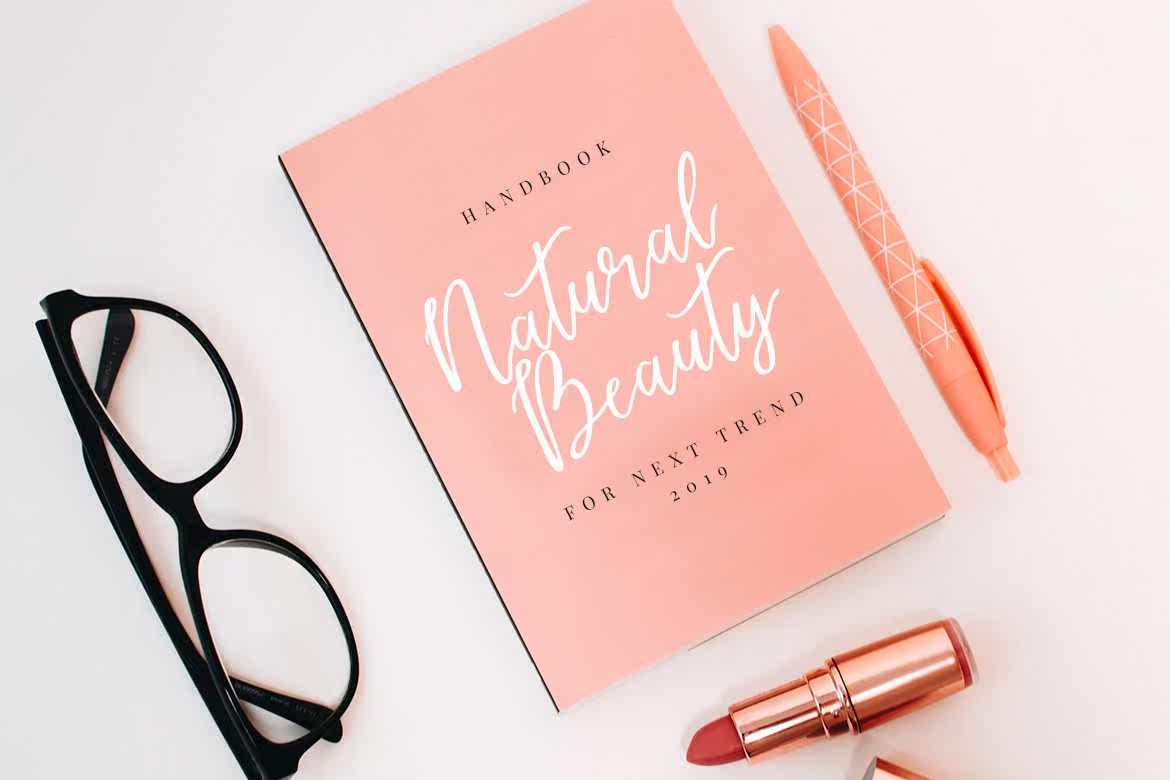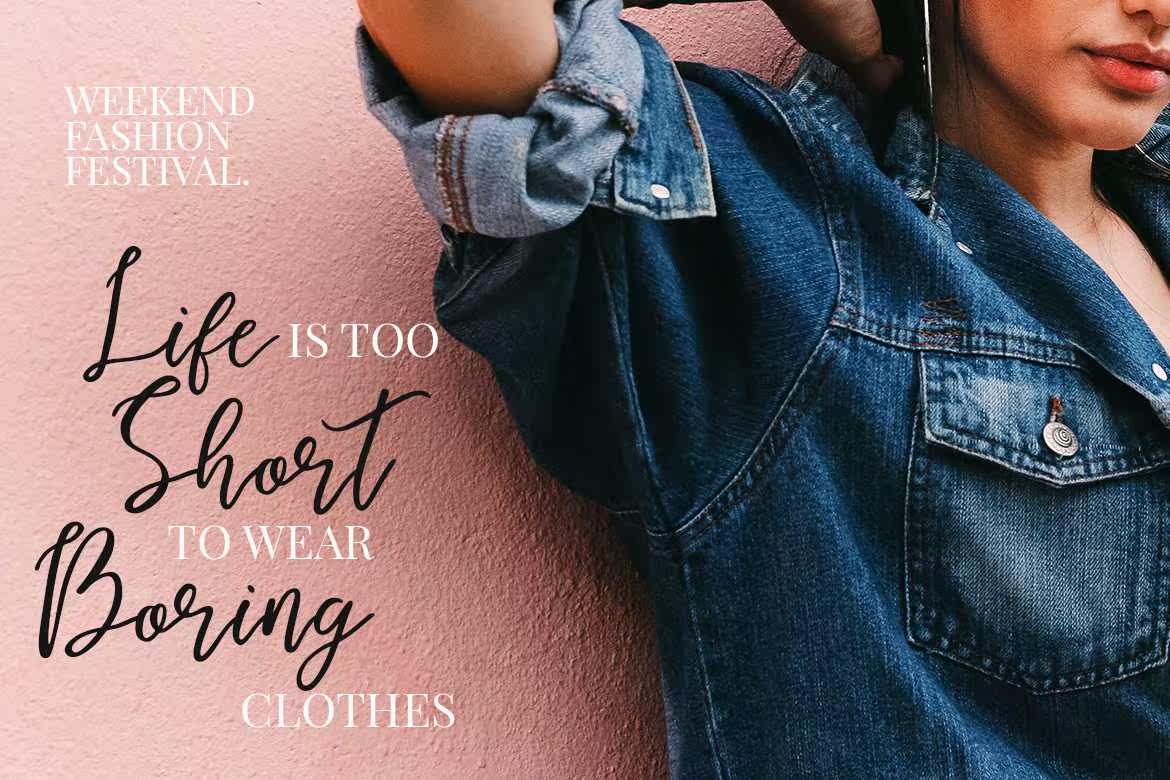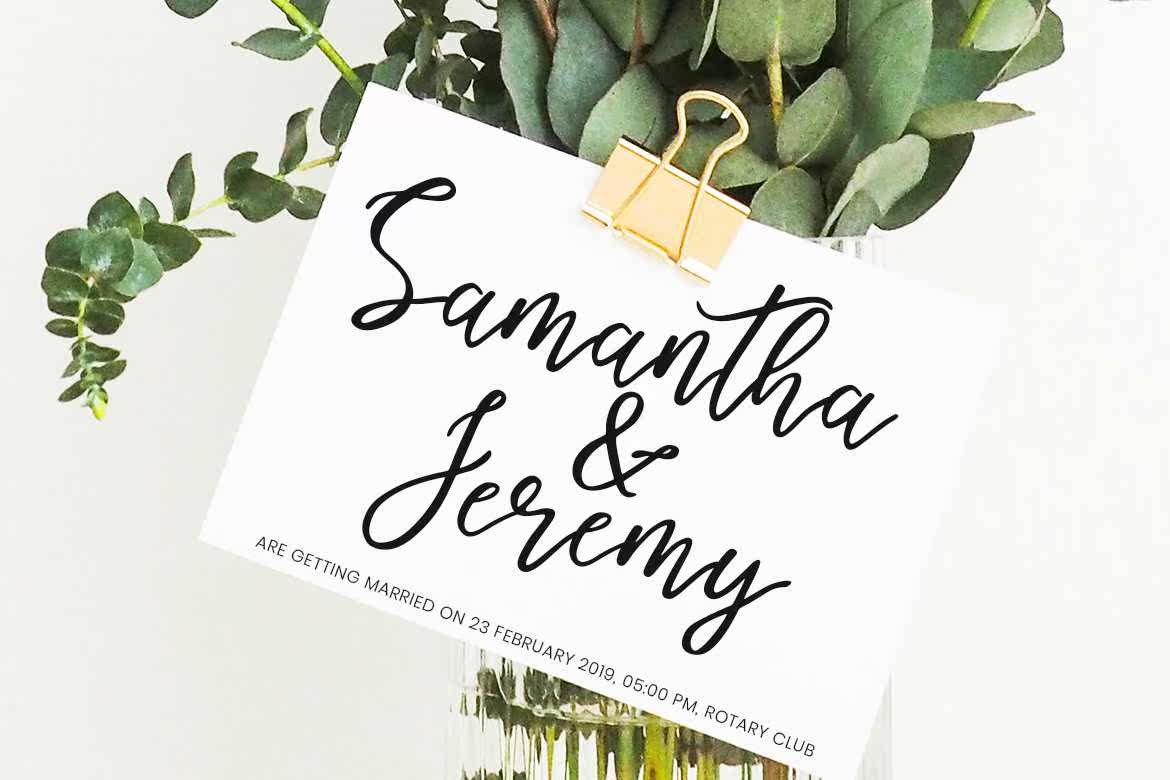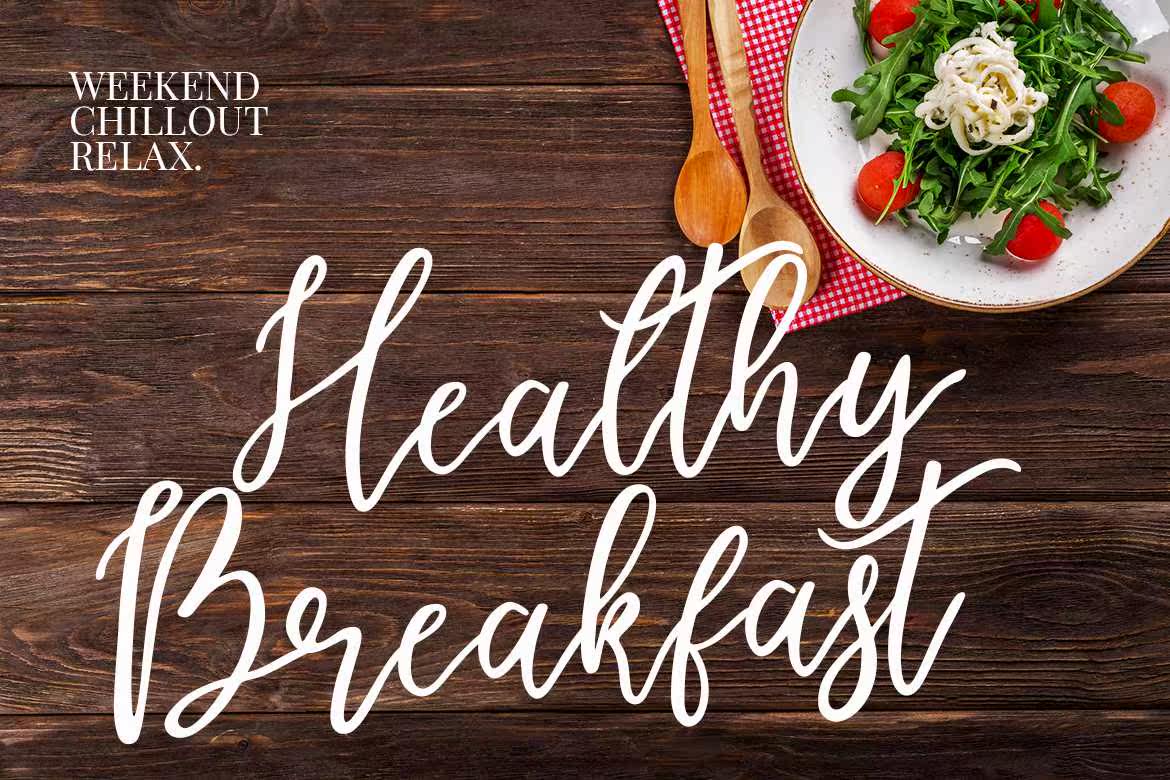
EndestrySasweet、Tricky、BounceyandModernCalliphyScriptFont,可通过个性化触摸设置最新项目的外观。EndestrySasweet、Tricky、BounceyandModernCalliphyScriptFont,可通过个性化触摸设置最新项目的外观。EndestrySasweet、Tricky、BounceyandModernCalliphyScriptFont可通过个性化触摸设置最新项目的外观。